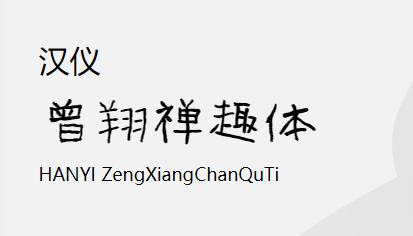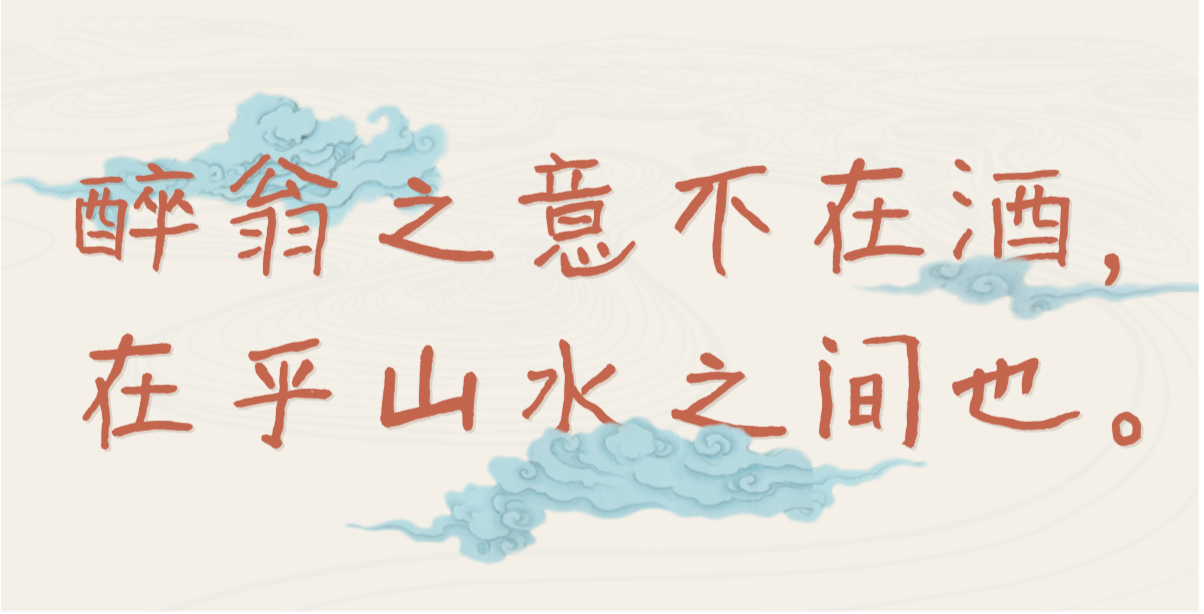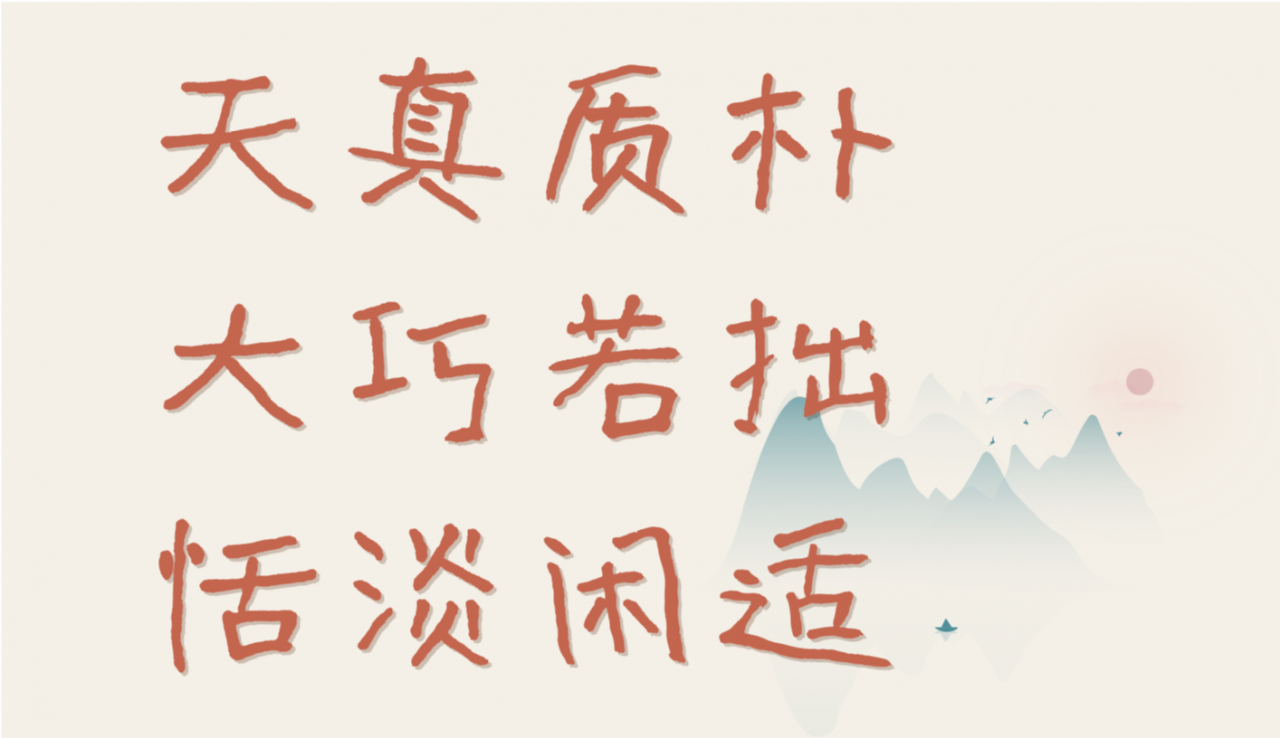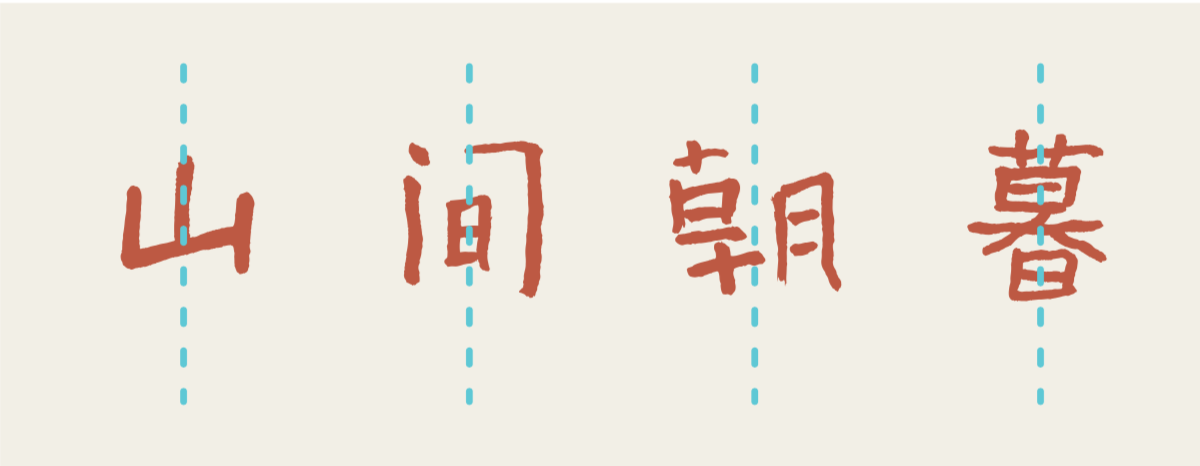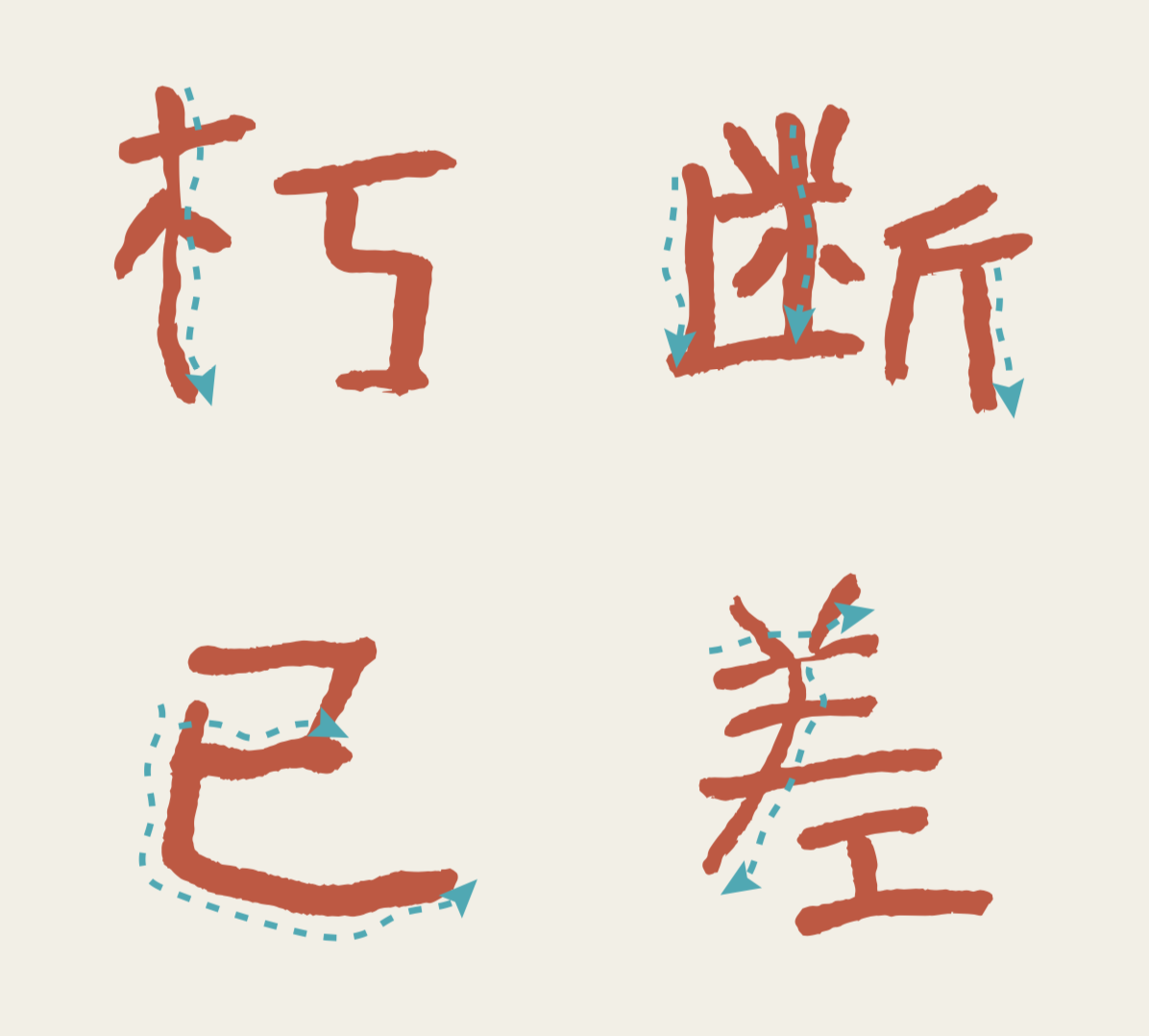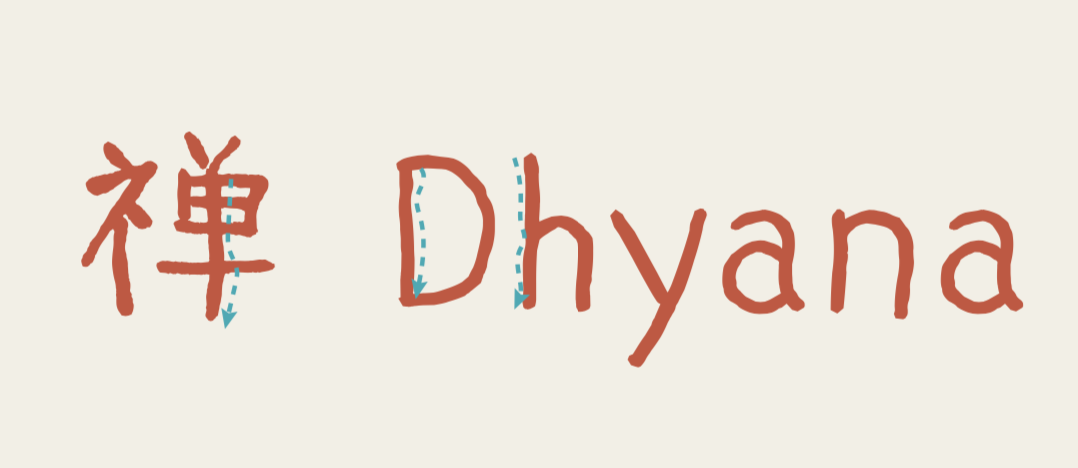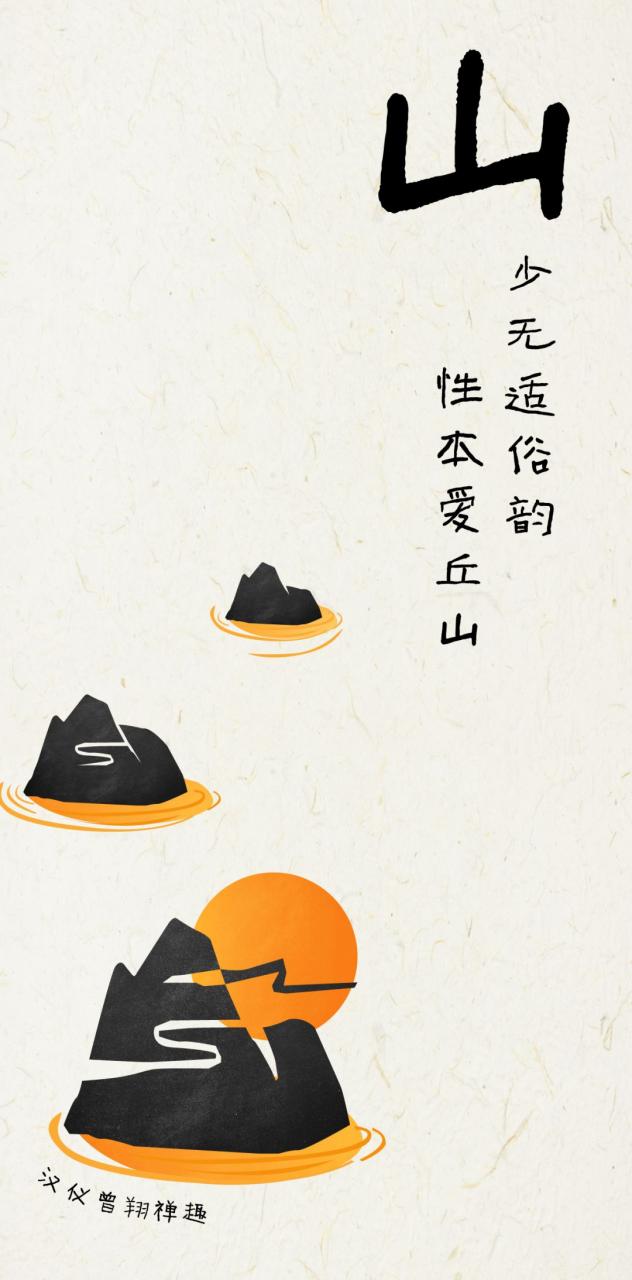
汉仪曾翔禅趣体W
作者介绍
曾翔毕业于解放军军事学院,从一名普通军人到享誉当代书坛的书法家,师从王任、刘炳森、沈鹏先生,打下了深厚的书法根基。被公认功夫过硬,结构造字能力强,笔性佳,并以其鲜明的艺术个性辉映了当代书坛。他是个智者,书艺精于诸体,转益多师,又能独辟蹊径,放胆变通。
曾翔的作品风格在当代书坛可谓特立独行,具有飞扬的个性、强烈的时代感,同时又深入传统,融诸体之长而求其通变。
如果说,现代构成是书法现代性的形式标志,而平民化则是现代艺术最典型的精神特征。从这种意义上说,曾翔书法中所体现的平民精神和民间格趣,使他成为先锋书法艺术阵营中最具代表性的书法家之一。
整体特点
印象派画家高更曾在致斯特林堡的信中说:“文明让你受苦,野蛮让我返老还童”,这句话用在曾翔的字体上倒是十分恰当。与传统文人创造的经典帖学相比,“汉仪曾翔禅趣体”无疑是“野蛮”的,有失“优雅”的,但却是充满活力的。朴拙、欢愉、天真、快乐,构成了“汉仪曾翔禅趣体”的品质,通过字体似乎能听到曾翔先生下笔时爽朗的大笑和发自内心的“好玩”的感叹。
总体来看,这款字体天真质朴,大巧若拙,含而不露。字体点画丰富,或取其疏朗洒脱,或取其茂密遒实,在大小相间、摇曳跌宕的零知己之中求得一种大秩序、大统一,适用于多种场景。
“汉仪曾翔禅趣体”的部件灵活多变,即使是相同的偏旁部首,不同的字也有不同的笔画形态。
结构特征
“汉仪曾翔禅趣体”的结构在奇中求正,笔画排布看似随意,却又巧妙的维持了平衡,这让每一个字都具有独特的趣味。
笔画特征
“汉仪曾翔禅趣体”的笔画提按过渡明显,线条灵动活泼,粗细相间,使字体富有动感,整体效果显得愉乐欢快。
中西文匹配
“汉仪曾翔禅趣体”的西文字母充分吸收了中文笔画和线条的特点,形成了带有朴拙韵味的字母。中、西文搭配使用时呈现出更佳的视觉效果。
应用展示